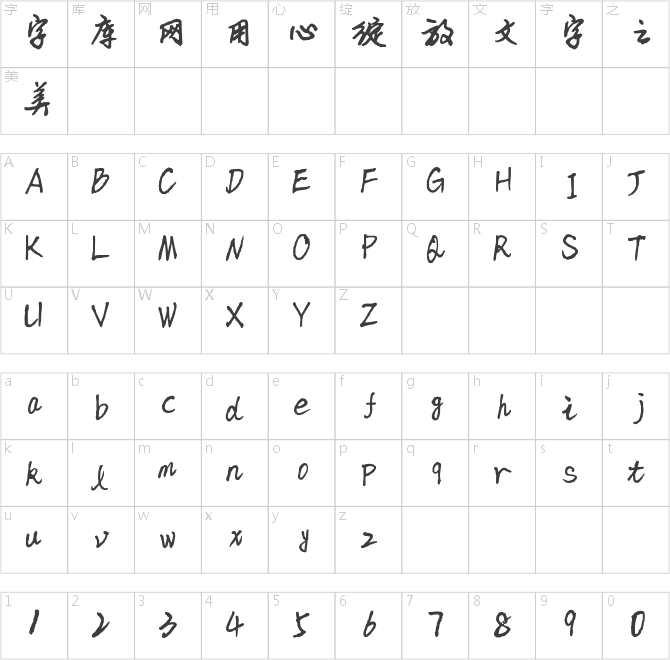
字體名稱: 張勃鋼筆體
張勃鋼筆體
張勃鋼筆體是以行楷的體勢為基調,區別于傳統的書法字體,更為注重線條的粗細變化,字體柔中帶剛,從而豐富字形的節奏感使字體更具藝術感和手原筆手寫痕跡,更貼近于真實感官享受
張勃鋼筆體字體字庫是一款讓人賞心悅目、百看不厭的中文字體,適合各類廣告和產品包裝設計應用,字體大小3.68MB,格式為ttf字體,上傳用戶是得·岸,作者/版權方為張勃